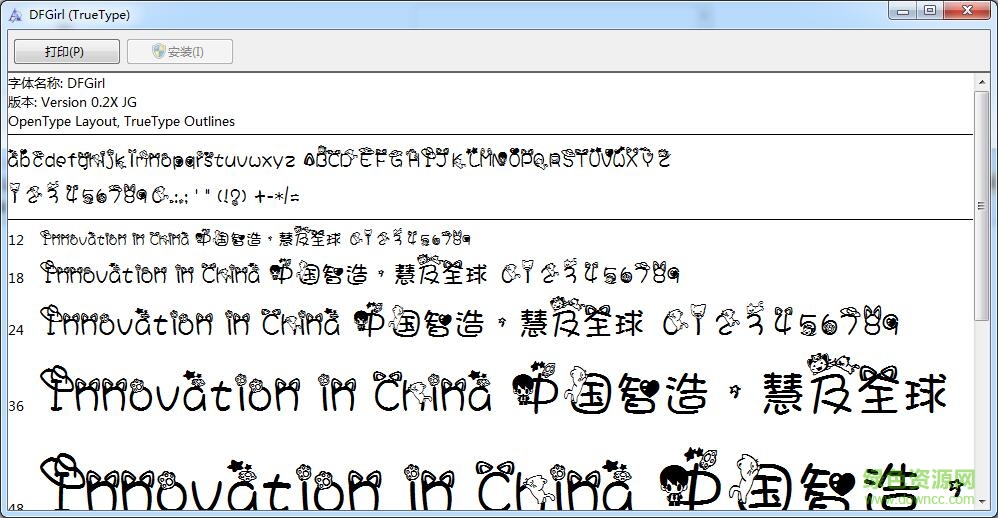
腹黑獸人攻體
腹黑獸人攻字體是一款可以用于美術(shù)設(shè)計(jì)的可愛(ài)字體。外形和貓咪字體長(zhǎng)相差不多,字體風(fēng)格比較活潑,喜歡這款字體的朋友快來(lái)綠色資源網(wǎng)下載吧。
字體介紹
腹黑獸人攻字體是一款用于腹黑設(shè)計(jì)方面的字體!這款字體屬于卡通風(fēng)格,字體比較生動(dòng)活潑,多種字體供你選擇!馬上來(lái)綠色資源網(wǎng)下載體驗(yàn)吧。
腹黑獸人攻字體